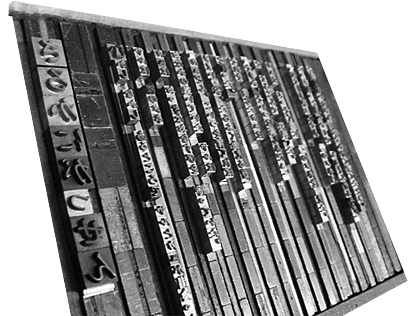
「写字」和「书法」
有这样两个词汇:「写字」和「书法」。在小学[1]里,「写字」是语文课程的一部分。将这个课程的目标大胆地概括起来,应该是以下几点。这些目标和活字字体设计其实有一些共通的部分。
- 字要写得正确
- 字的形状要写得端正
- 写出来的文字要易于阅读
中学的语文课程里面仍旧包含写字。小学阶段只有楷书,到了中学加上行书,还会要求汉字和平假名、片假名能互相搭配。根据目的和必要性,搭配地写出字来,易于阅读,而且要有一定速度。因此,中小学里面只是「写字」而已,并不能算是「书法」。
到了高中,美术课程里面有「书法」课了。说到「书法」,其目标与语文课的「写字」就完全不同了:
- 书法 1: 通过广泛的书法活动,培养对书写的兴趣爱好,并且丰富感性认识,提高书写能力,培养表达和鉴赏的基础能力。
- 书法 2: 通过诸多的书法创作活动,培养对书写的兴趣爱好,并且提高感性认识,加深对书法文化传统的理解,培养富有个性的表达和鉴赏能力。
- 书法 3: 通过诸多的书法创作活动,在培养一生对书法的兴趣爱好,并且尊重书法文化和传统的态度的同时,磨练感性,培养富有个性的书法能力。
写字和书法二者都和活字字体设计有联系,从活字字体设计的基础来考虑的话,应该对「写字」课程的目标进行深化。
在没有现代印刷的时代,碰到一本想要读的书,必须借过来一个字一个字地认真抄写。这可需要极大的耐心。现代看来,要抄这么多本书简直是不可想象,但在当时是司空见惯的事情。在中国在欧洲都是这样。
能抄写的不仅是文章。在中国还有一种习惯,就是连书写风格也一起复制下来:临书、向拓、双钩填墨等等,都是常用的方法。
所谓临书,就是照着原本写。为了练习照着样本书写,还分三个学习阶段:单纯模仿形状的「形临」、能把样本的意境心髓都抄下来的是「意临」、不看样本都能写的是「背临」。所谓向拓,是垫着样本抄写。把薄纸盖在原本上复写的这种手法难免都会留下抄写人的笔迹导致副本和原本不同的印象。
最忠实于原本的复制方法应该是双钩填墨。所谓双钩,就是在文字上覆盖上薄纸描绘轮廓的意思。然后用墨在轮廓内部涂满,就是所谓双钩填墨了。对于双钩填墨法,一些书法界人士有批判性意见,但碑刻、版刻上描轮廓可以比较容易地再现书写风貌。通过这种技法的应用,轮廓得到逐渐修正,文字具有了公共性,可读性和可识别性都提高了。
木版印刷
一字一字地抄写,工作量很繁大,于是后来就出现了将文章全部刻在木制版块上印刷的方法,称为「木版印刷」。由于需要直接在木板上着墨,再用马楝印刷,因此必须刻镜像反转的文字。
木版印刷先由「画师」用墨在薄纸上写好文字和图案,这称为底稿;之后把底稿放在版木(樱花树、枫树、梨树、朴树、黄杨、梓树)上,有时还要上一点稀浆糊。底稿的图文当然都是反转的。之后就轮到雕刻师登场。雕刻时使用版木刀、三角刀、圆凿和平凿四种工具。雕完之后把剩下的原稿纸冲洗掉,再用雕刻刀淘一遍。为防止墨水晕开,印刷师先把纸用矾水处理过后贴在版木上,然后用马楝[2]认真地在纸背进行刷擦。之后进行配页、切齐毛边等工序,加上封面最后装订成书。
虽然量产变得相对容易了,但雕刻版木依然要花费很多功夫。如果要忠实再现毛笔的运笔,则要花费很长时间,而且无法分工合奏。在中国的宋代,工匠们钻研出了一些既容易雕刻又易于阅读的字体。
另外,石版画、铜版画、孔版画[3]等方法听起来更像是美术领域事情,但这些方法同样可以用来书写记录文章,也就是石版印刷、铜版印刷、孔版印刷。
所谓活字
书籍这样长篇的文章,同样的文字会重复出现,所以想把之前雕刻的东西拿来再利用,也是很自然的事情。于是就出现了把零碎的一个字一个字组合起来的做法,这样的每个零碎的字就叫活字。把活字摆在一起来做成版面就是活字版。
英语里面活字称为 type,活字字体叫 typeface。活字中,最常用的是使用铅、锑、锡合金制造的,除此之外还有木活字(wooden type)、金属活字(metal type)、照片活字(photo type)、数码活字(digital type)等等。在中国甚至还有泥活字、磁活字等等。
活字印刷是「活字版印刷」的简称。金属活字也好,照片活字也好,凸版也好,平版也好,只要用的是活字,就都可以称为活字印刷。活字版也称为「聚珍版」。这个名称是中国清朝《四库全书》活字版善本完成时乾隆皇帝所赐。
另外,照片活字的称呼可能大家不太习惯,但是照片排版用英文说就是 phototypesetting,照相排版机就是 phototypesetter。要是把 typesetting 翻译成活字排版,那么 phototypesetting 就是照片活字排版了。金属活字的 Monotype(蒙纳自动铸排机)也是这样,现代的个人电脑在某种意义上也是一种活字排版机。
活字字体
制作活字字体时,为了对应各种文章,需要事先将所有的文字设计出来。这和所谓的「美术字」不尽相同[4]。
到现在还有人认为活字字体是自古以来就有的,或者是机器自动做出来的。然而实际上它们都是人工手绘制作而来,即便是数字时代的当今依然如此。
手写本,本身就是手写出来的,每个人有每个人所谓的笔迹,是有个性的。而刊本是将手写的东西经过雕刻以后样式化的,所以所谓个性在某种程度上受到限制。于是文字就以活字字体的方式逐渐规格化起来。也可以说是单纯化、合理化。
活字字体并不是从书写直接转化过来的,中途必须经过雕刻的工序。制作活字字体必须经过雕刻这道工序。正是从书写到雕刻的转化导致了字体的样式化。然后再进行加工让它更为合理,增加判别性和可读性。
易认性是指是否能容易分辨出与其他文字的差异,因为单纯手写的话是很容易认错的。易读性是指是否容易阅读,排成文章之后是否会给读者视觉造成负担。为了不让读者在阅读时有压力,需要将大小粗细做整齐。
易认性、易读性和诱导性被称为字体选择的三要素,在字体设计中也是需要重点对待的。
字形
「字体」(日语:書体)和「字形」(日语:字体)的区别也是比较麻烦的[5]。所谓字形(日语:字体)在日本《大辞泉》里面是如下解释的:
- 【字形】
- 笔画组合而成的文字的形状。定型化的笔画组合。一个字根据笔画数的区别,有正字、俗字、新字、旧字的不同。
- 同「字体(1)」。
「字形」应该按照第一种解释来用,这样不容易混淆。尽管如此,字体和字形的确有很深的关系。随着字体的变迁,字形和笔顺也发生变化。篆书不能用楷书的字形来写,近代的明朝体用写字用的楷书字形来写也会有所不适。
字型(font)
人们经常把活字字体称为 font[5]。多数人对于书籍使用的字体称为活字,对电脑称为 font。同样在日本《大辞泉》里面写的很清楚:
- 【字型】(Font)
- 同一字体某特定大小的大小写字母、数字、记号等一整套活字。
据说 Font 原本是 IBM 公司打字机活字存储媒体的商品名,所以在活字存储媒体的层面上说也不算错,但很明确的是,字型不是活字字体。
金属活字
以印刷为目的的金属活字需要开阔的拣字场所。无论如何都需要预先坐好大量的活字备用。举例来说,本文若以五号明朝活字排印,那么需要整理、排列大约一万种不同的活字。而且,频繁出现的文字有必要准备上十来个,这样的话,即便只使用单一字体的单一字号也会需要大量的活字。
光有五号明朝体活字还不够,标题处应该会用上五号黑体活字,至少也会想用二号明朝体活字。只是这一来所需的空间也就翻了三倍。使用于标题的活字,并不需要那么多不同的字符,不过尺寸会增大。在拣字场,有许多立体排列好的活字箱,活字按照部首分类,正文字体位于标题字体下方。
从这些活字箱中,按照原稿挑拣出来活字,排列到称为拣字箱的小容器里。从事这一工作的人,称为拣字工。专业拣字工可以挑拣一千三百字以上。熟练的拣字工会将常用字集中放在一个箱子里,也能凭经验熟记排字箱的番号,从而以最短的移动距离完成排字。
拣字箱继而转送排字场,箱中的活字与空铅(quadrat)及行间空(inter lead)、格线等辅助金属块组合到一起,排列成为原稿指定的形制。排字工人左手握着排字手托(stick),将选字箱中的活字像插秧一样植入排好。排列好一行之后,把确定行高的空白铅条(inter lead)放在行间,再排列下面的一行。排好的字转移到所谓木盘(galley)上面,用麻线牢固地围绕捆绑好。
除了用于拼版之外,也有专门用于储存已排好之版面的拼板台存在。但是这项工作一般来说是由纸型(flong)来完成的。纸型是将特殊的纸用已排好的版面压制成的铸模。在其上浇注融化的铅,即可铸造出用于印刷的铅版。纸型重量很轻,保存也容易,需要制作铅版的话,无论什么时候都可以再版。
原来的活字版使用后经过清洗即可拆版,然后一字一字地送回到活字箱中,以便下次印刷时重新选字。对熟悉这一工作的拆版工人来说,这并不是一件费力的事情。磨损而不能使用的金属活字会被融化,重铸为新的活字。
金属活字的消亡恐怕是大势所趋。不过,虽然金属活字消失了,活字字体仍旧会作为电子活字延续下去。金属活字、照相活字、电子活字,活字字体的承载方式和构造与时代一起变化着,但是优秀的活字字体却是无比长寿的。
照相排版机用文字盘(写研公司的情况)
照相排版机(phototypesetter)使用的是照片活字(photo type),一般称为「文字盘」,是在蚀刻有文字的玻璃板上覆盖一层遮光物,然后再加盖一层玻璃制成的。为了使其轻量化,似乎也有在表面涂一层保护膜的方法。
作为在照排机体内固定文字盘的一种方法,在1957年(昭和32年)发表的 SK-3R 型机种采用能更换字体种类的「中框固定式」开发。此后的角宿一-S型号改为采用「指针式」文字盘,更换字体更加容易,精度也提高了不少。
文字盘包括有「主盘」和「辅盘」。角宿一-S 起先采用一系列包含 269 字的小型文字盘,后来开发出可以单长容纳 2862 字的大文字盘,被称为「主盘」,而以前的小型盘改称「辅盘」。1969 年(昭和四十四年)发表的帕博-J型可以搭载 7Q 到 100Q 的文字盘,并且具有自动西文字尺寸调节装置。1965 年(昭和四十年)发表的萨普顿-N自动照排机器采用圆形的文字盘,使用用钻孔胶带进行输入,可以高速地输出排好的版面。总之,自动照排机的文字盘仍旧是属于模拟技术。
照排文字盘也走向了终结。活字字体,必须依照存储媒体的变化而重新设计制作。这样一来,这些字体最终得以通过数字化的形式延续生命。
数字化字体(写研公司的情况)
电算排字机通常是指称光学(模拟)式的排字机器。光学式机器利用文字盘将电子信号转化为文字。而完全数字化的机种称为电子排字机,也就是使用数码方式存储数字字体的机种。写研公司 1977 年(昭和五十二年)发表的 SAPTRON-APS5 是最早的此类机器。
SAPTRON-APS5 采用数码字体(电子活字),将许多小点像棋盘格子一样排列成点阵来存储字形,是用黑白来代表各点(网格,mesh)的二进制位图方式。电脑的显示器和打印机的印刷,最终其实都会以点阵表现。所以文字的原数据作为点的集合也会是这个形式。有简单地存储并回放全部点阵的低像素存储法,以及使用游程编码的压缩算法在输出时复原字形的高像素存储法。不需要复杂演算的位图方式能很快地被显示出来,不过不具备扩大或缩小的能力,字的轮廓也有所损毁,而且分解得太过细小的话,数据量会变得相当庞大。通常像素比较少时以全点阵存储,像素时则使用能大幅压缩数据量方法存储。
位图方式无法在特大尺寸的字体上使用。为此必须想出用矢量摘要的方式存储字体的办法,也就是让字型的轮廓线(Outline)与直线(矢量)近似。不过,这个方式对西文字体很有效,应用于像汉字这样复杂的文字体系时,数据量会增加。为此,高次曲线(如样条曲线、贝塞尔曲线、柯尼卡线以及圆弧线)也用来记录轮廓线。输出字体的时侯,将轮廓线内侧填充颜色,即可显示字体的外廓曲线。
最早作为由矢量曲线方式存储的日语字体,是 1983(昭和五十八)年时写研公司发表的 C 字体。实际被广泛采用了的矢量日本字体包括 1985(昭和六十)年发表的 SAPTRON-Gimmy 和 SAIVERT-H 等。
早期的字体以磁存储媒介(8 英寸,5 英寸,3.5 英寸的软盘等)保存,而据说在 1985 年(昭和六十年)时写研公司在世界上第一次用 CD 光盘收录了 MASALA-P 型日文商用字体。
本文译自日文,故中小学教育情况自然说的是日本中小学,之后的高中美术课书法教育目标,也是援引日本的教学大纲。
马楝 (liàn),是一种日式印刷工具,现代多用于版画。功能类似于滚筒,但形状为圆饼形漆器芯,外面用细竹皮捻起包住以增加平滑度。
孔版画:以挖空硬卡纸透过颜料着色的绘画方法。
原文为「レタリング」,即英文 lettering 的片假名。Lettering 在英文中一般指描绘、印刷字体的过程。
日语中有三个词,「書体」、「字体」、「フォント」(font 的音译)。考虑到跨语言的问题,从汉字词汇使用状况出发来,此处将「書体」译作「字体」,将「字体」译作「字形」,也就是「字体的形状」,而「フォント」译为「字模」。